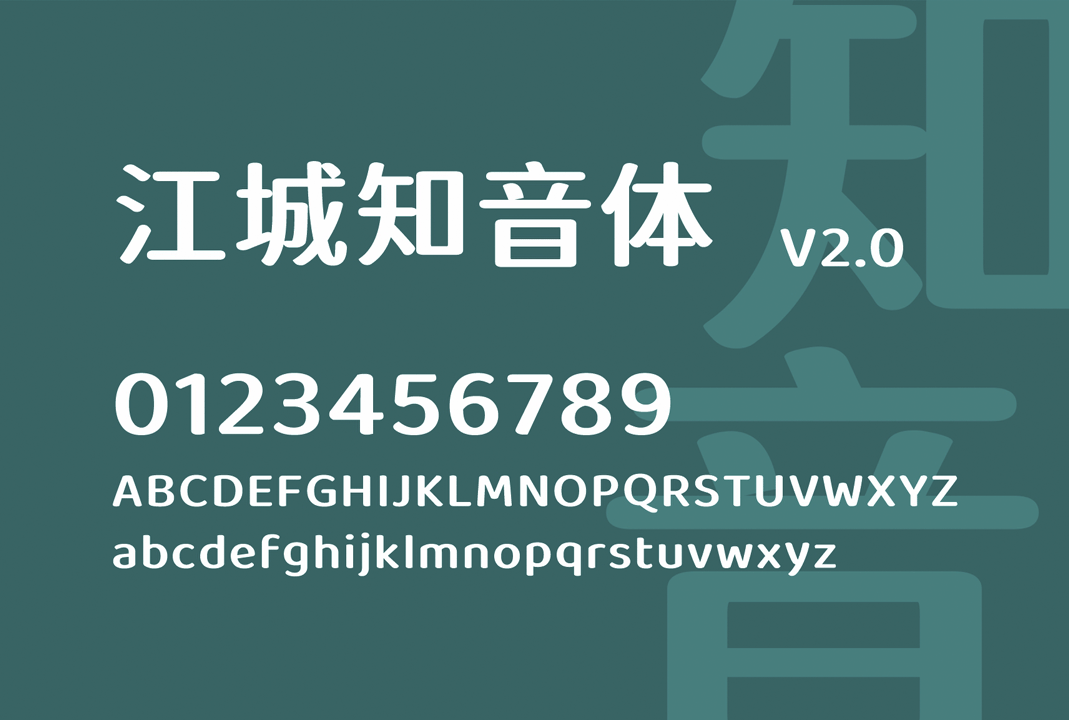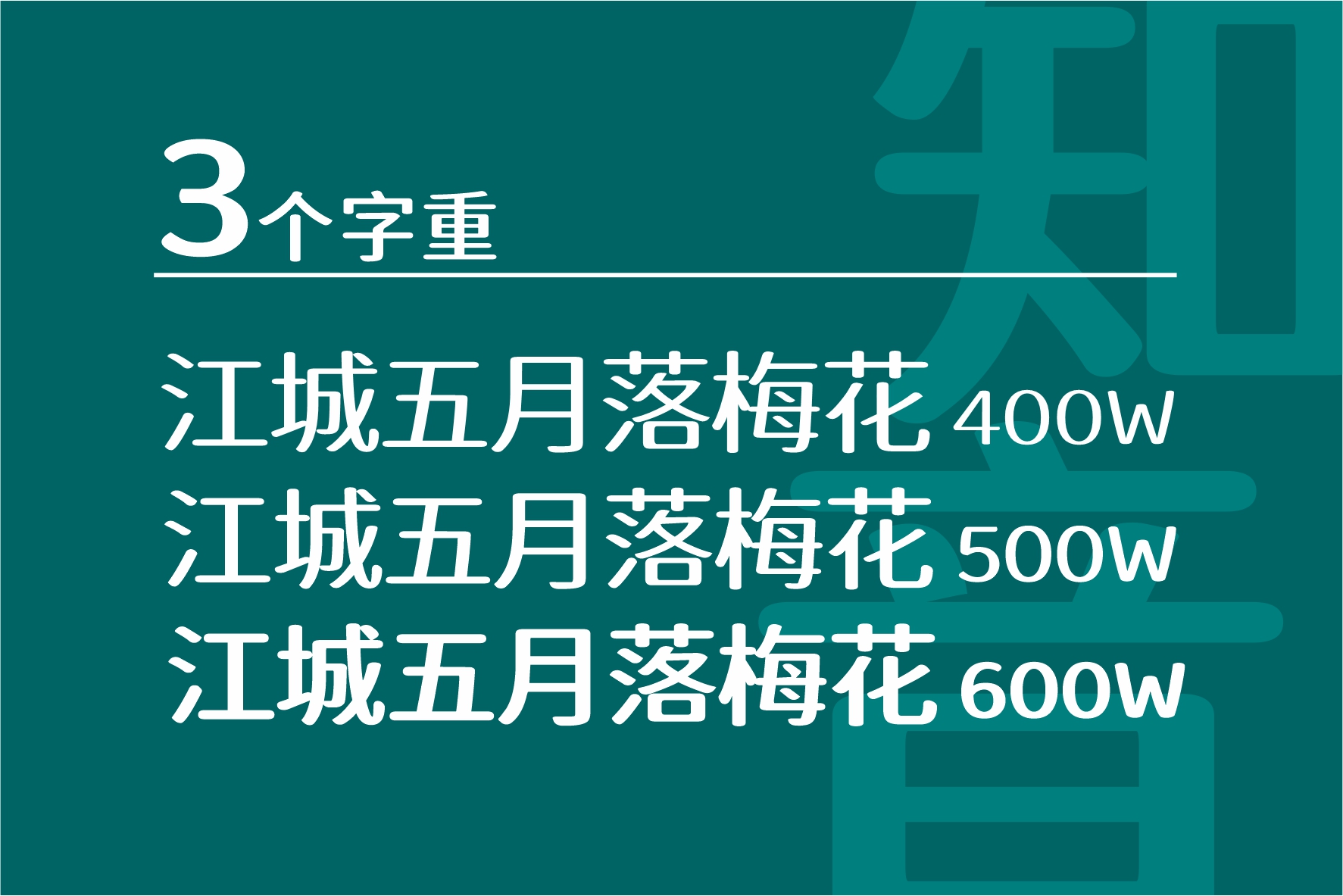
江城知音体(v2.0)是由微博网友(@设裂星辰)发布的一款可免费商用的中文圆体字库,该字体拥有3个字重。
江城知音体是基于江城圆体(江城圆体基于思源黑体)改造而成,作者将江城圆体横笔减细处理,纵笔增粗处理而成,字体笔画横粗竖细的风格颇为特别,适用范围广泛。
江城知音体拥有超大的字符集,所以无论是简体还是繁体都基本上不缺字,能满足绝大部分的设计需求。